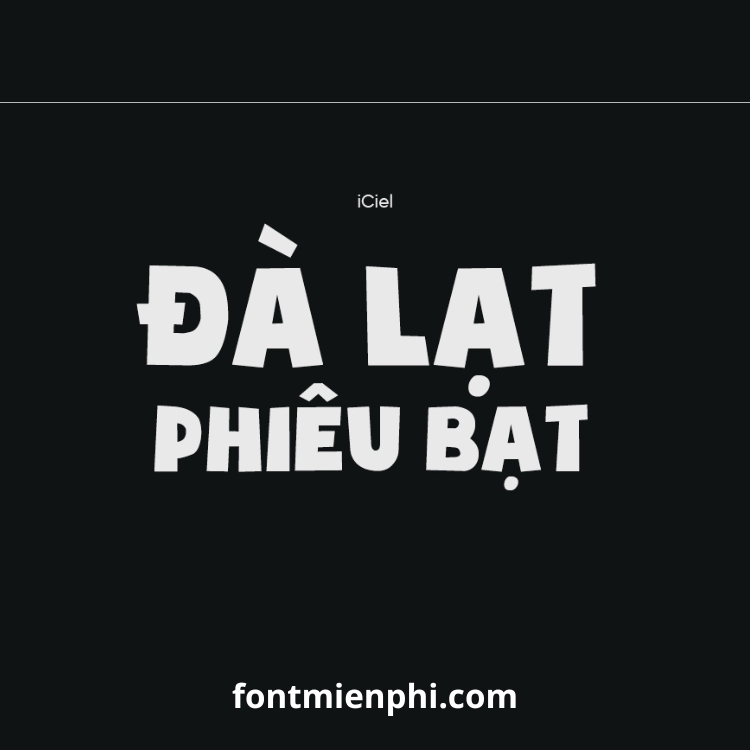
Việt hóa font iCiel Soup of Justice
Việt hóa font iCiel Soup of Justice – Phong Cách “Mạnh Mẽ Đến Từng Nét Chữ”
Giới thiệu nổi bật:
iCiel Soup of Justice là font chữ display việt hóa với phong cách mạnh mẽ, góc cạnh, lấy cảm hứng từ những tựa game hành động và phim siêu anh hùng. Font chữ này đặc biệt phù hợp cho các thiết kế cần tạo ấn tượng mạnh và thể hiện sức mạnh, sự quyết đoán.
Đặc điểm ấn tượng:
Nét chữ đậm, góc cạnh – Tạo cảm giác mạnh mẽ, phù hợp với phong cách gaming, thể thao
⚡ Hỗ trợ đầy đủ tiếng Việt – Giữ nguyên vẻ đẹp của font gốc khi sử dụng tiếng Việt
2 phiên bản (Regular và Outline) – Linh hoạt cho nhiều phong cách thiết kế
Ứng dụng sáng tạo:
• Thiết kế logo game, esports
• Poster phim hành động, siêu anh hùng
• Ấn phẩm truyền thông thể thao mạnh mẽ
• Thiết kế áo game thủ, streetwear
iCiel Soup of Justice – “Chọn sự mạnh mẽ, bỏ qua những nét chữ nhạt nhòa!”
✔ Phù hợp nhất cho tiêu đề ngắn, slogan
✔ Nên sử dụng kích thước lớn để thể hiện rõ nét đặc trưng
✔ Kết hợp hiệu ứng grunge, metal để tăng độ “chất”